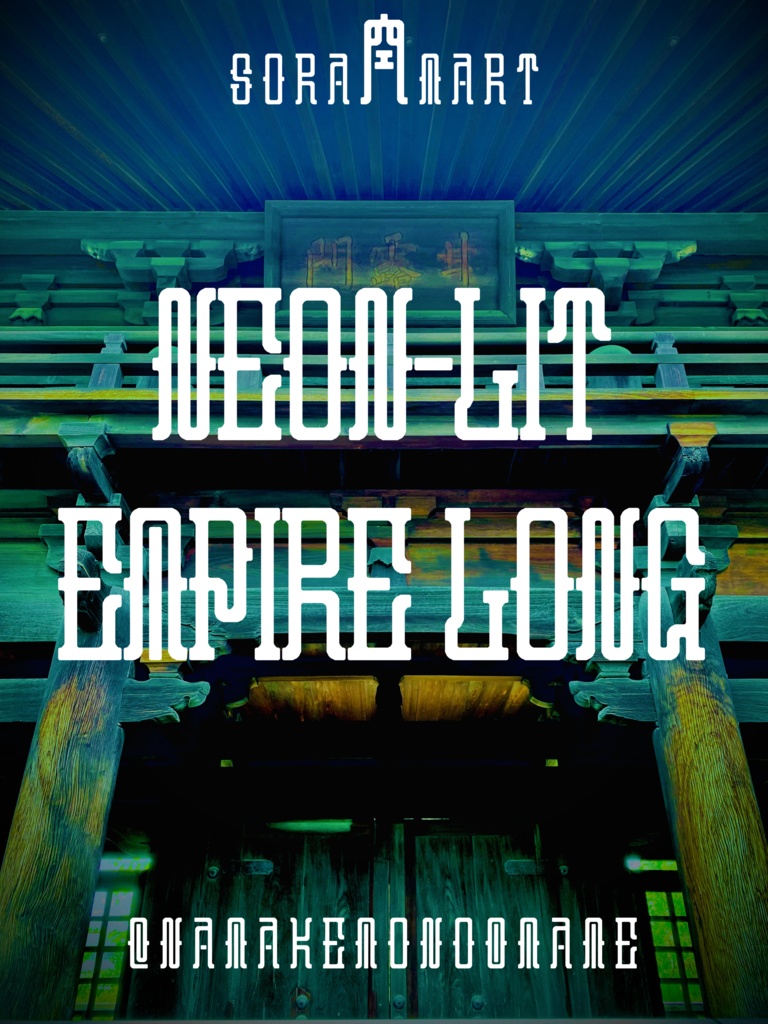
そらマートフォントデータ”Neon-Lit Empire Long”Digital2,500 JPY放入購物車Buy a GiftAbout Gift”篆書体”をモチーフにしたサイバー調フォントの縦長アレンジ版 "Neon-Lit Empire Long" です。 「TrueTypeフォントファイル」という形式です。 ダウンロードした後、Zipファイル内のデータをインストールしてお使いください。 このフォントは商用利用可となっております。 お客様の制作・創作活動のお役に立てれば幸いです。 ※使用上の注意事項などは、添付のReadmeをお読みください。そらマートVisit FANBOX!Fontsフォントデータ”Pretty Commando”そらマート0 JPYFontsフォントデータ”Abyss Dive Punk Retro”そらマート2,500 JPYFontsフォントデータ”Abyss Dive Punk Wide”そらマート2,500 JPYFontsフォントデータ”Abyss Dive Punk”そらマート2,500 JPYFontsフォントデータ”Emerald Sphere Sprite”そらマート2,500 JPYFontsフォントデータ”Emerald Sphere Long”そらマート2,500 JPYFontsフォントデータ”Emerald Sphere”そらマート2,500 JPYFontsフォントデータ”Monolith Glitch”そらマート2,500 JPYFontsフォントデータ”Monolith Formula”そらマート2,500 JPYFontsフォントデータ”Rolling Cute”そらマート2,500 JPYFontsフォントデータ”Tricky Wire Merge”そらマート2,500 JPYFontsフォントデータ”Tricky Layer Wide”そらマート2,500 JPYFontsフォントデータ”Tricky Layer”そらマート2,500 JPYFontsフォントデータ”Popcorn Tab Plasma”そらマート2,500 JPYFontsフォントデータ”Popcorn Tab Heavy”そらマート2,500 JPYFontsフォントデータ”Popcorn Tab”そらマート2,500 JPYFontsフォントデータ”Tetra Pixel Dash”そらマート2,500 JPYFontsフォントデータ”Tetra Pixel Fluid”そらマート2,500 JPYFontsフォントデータ”Tetra Pixel”そらマート2,500 JPYFontsフォントデータ”Neon-Lit Empire”そらマート2,500 JPY查看更多